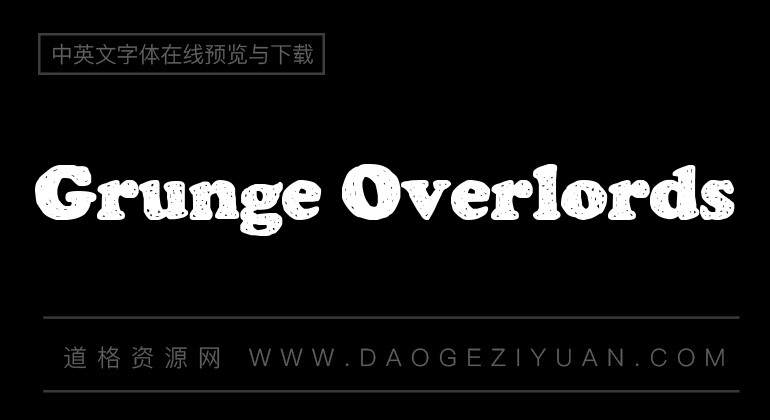
? Grunge Overlords 字体是一款借鉴 90 年代摇滚风格的手写字体,具有浓厚的摇滚气息,整体风格非常抢眼。字体的字母形状主要是由折线和曲线组成,具有粗糙的质感,较为抽象,但又不失细节,在细节上更具有个性。字体的笔画粗细不一,形成了活泼的视觉效果,具有较强的表现力,适合用于海报、展示等应用场景中。内容介绍
Grunge Overlords是一款非常不错的手写艺术字体,具有很好的视觉感,适合于文化类的宣传设计、商业类品牌的广告和产品包装设计以及个性化文字排版等较多场景。